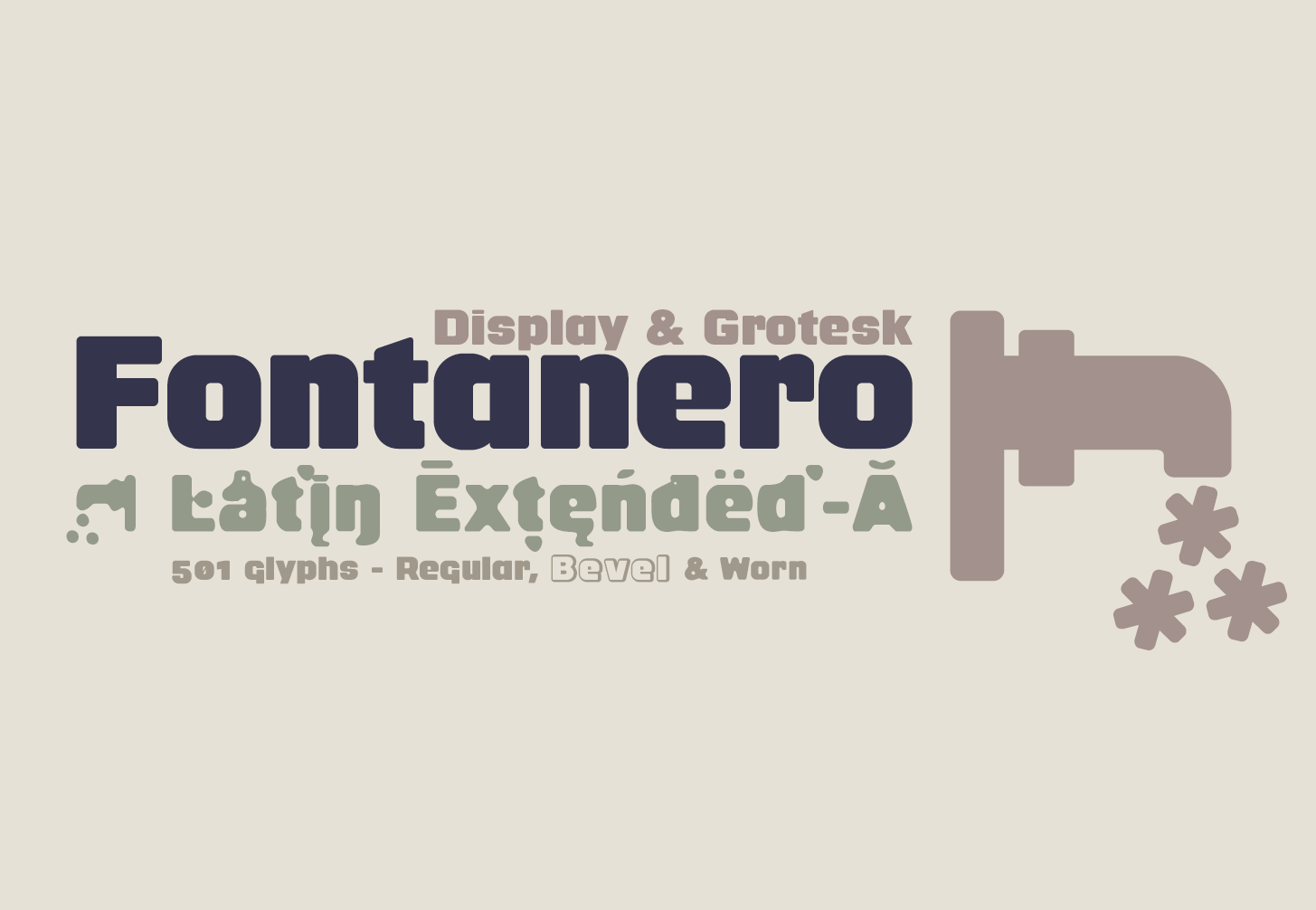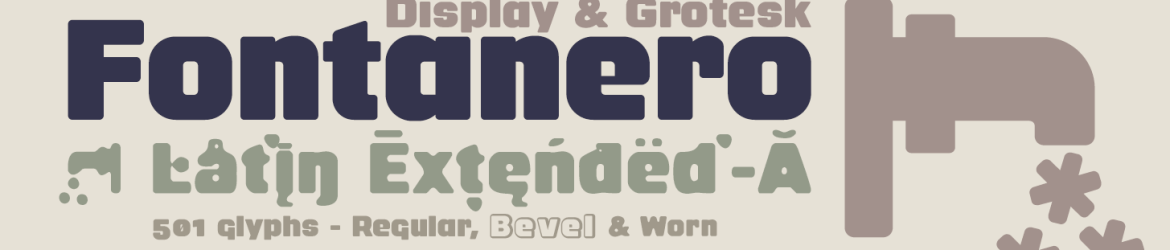
A Fontanero Font é uma elegante fonte sans-serif desenvolvida pelo designer defharo. Esta escolha de tipo tem proporções quadradas e antas redondas, oferecendo um estilo compacto que se destaca por sua proporção ascendente curta. O compromisso do designer com a arte geométrica e as sequências matemáticas relacionadas ao número áureo levou à criação desta nova fonte de exibição. Incluída na fonte está o símbolo da Bitcoin (b #). Este design abrange tanto uma versão completa quanto um licenciamento comercial, garantindo que qualquer projeto possa aproveitar sua sofisticação e criatividade. A Fontanero Font é perfeita para ambientes digitais modernos e criativos, proporcionando letraversões atraentes e funcionalas de forma arredondada em proporções quadradas.